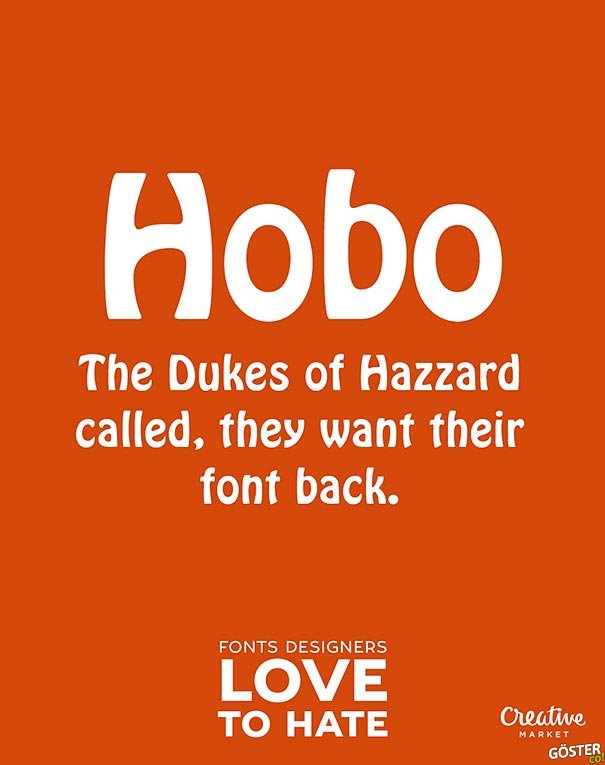
İnsanların Nefret Etmekten Keyif Aldığı 11 Yazı Tipi
Hobo: Çılgın Kuzenler filminin fontu. Demin aradılar, fontlarını geri...
İnsanların Nefret Etmekten Keyif Aldığı 11 Yazı Tipi
Hobo: Çılgın Kuzenler filminin fontu. Demin aradılar, fontlarını geri...
Hobo: Çılgın Kuzenler filminin fontu. Demin aradılar, fontlarını geri istiyorlar.